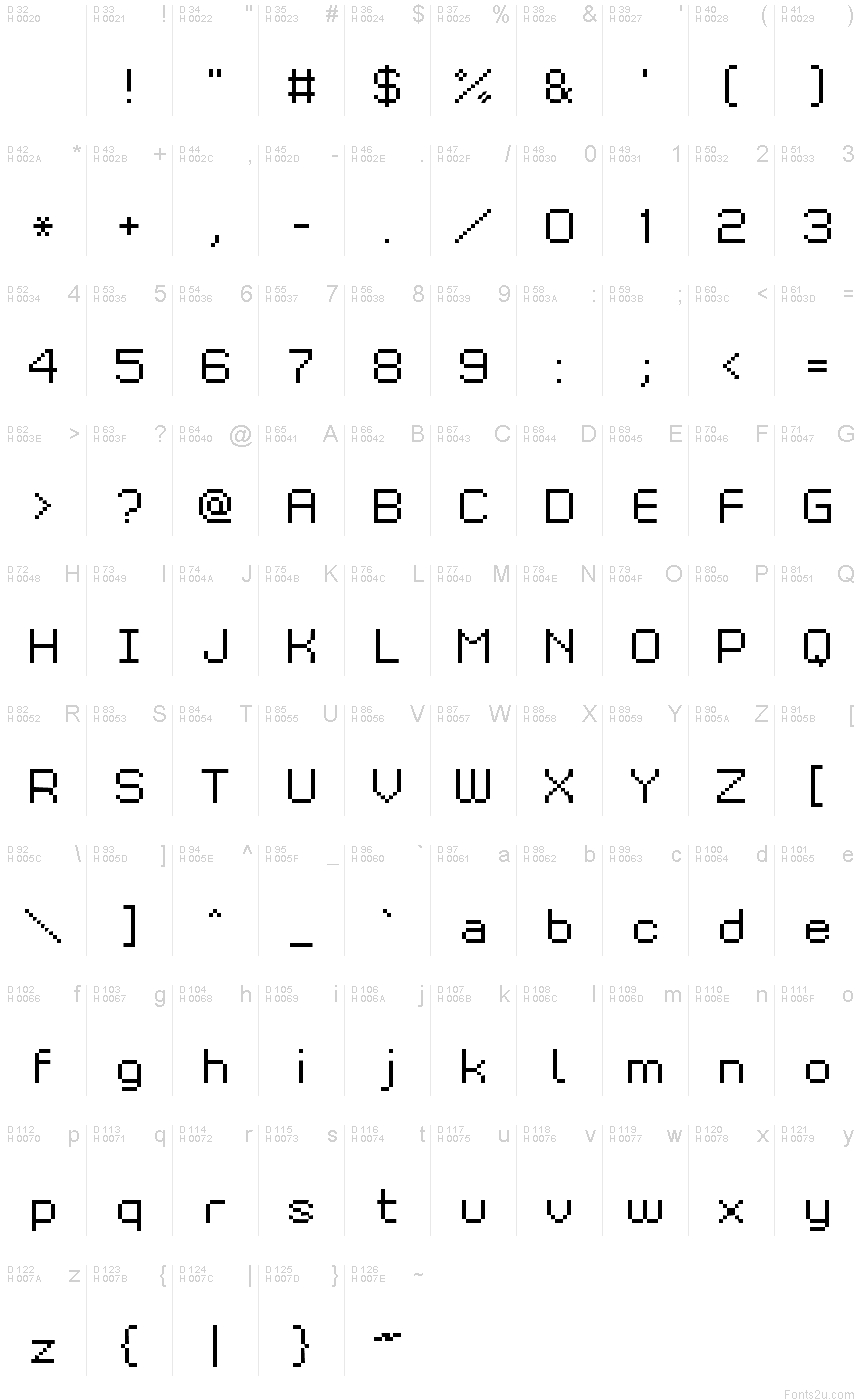
Podgląd czcionki Grixel Kyrou 9 Regular
Grixel Kyrou 9 autorstwa Nikosa Giannakopoulosa to darmowy, bitmapowy font pikselowy o surowym, arkadowym charakterze. Litery zbudowane są z twardych, kwadratowych stopni oraz otwartych, kanciastych cięć, co nadaje alfabetowi oszczędny, cyfrowy rytm, bliższy wczesnej grafice ekranowej niż wygładzonemu retro-pastiche.
Naturalnie pasuje do makiet UI gier, zinów technologicznych, napisów na plakatach, plansz tytułowych i kompaktowych logo, gdzie blokowa siatka jest częścią przekazu. Jako darmowy font świetnie sprawdza się również w krótkich nagłówkach, etykietach menu i monogramach, ponieważ sztywny układ pikseli sprawia, że każde słowo wygląda na przemyślane i precyzyjnie zakodowane.